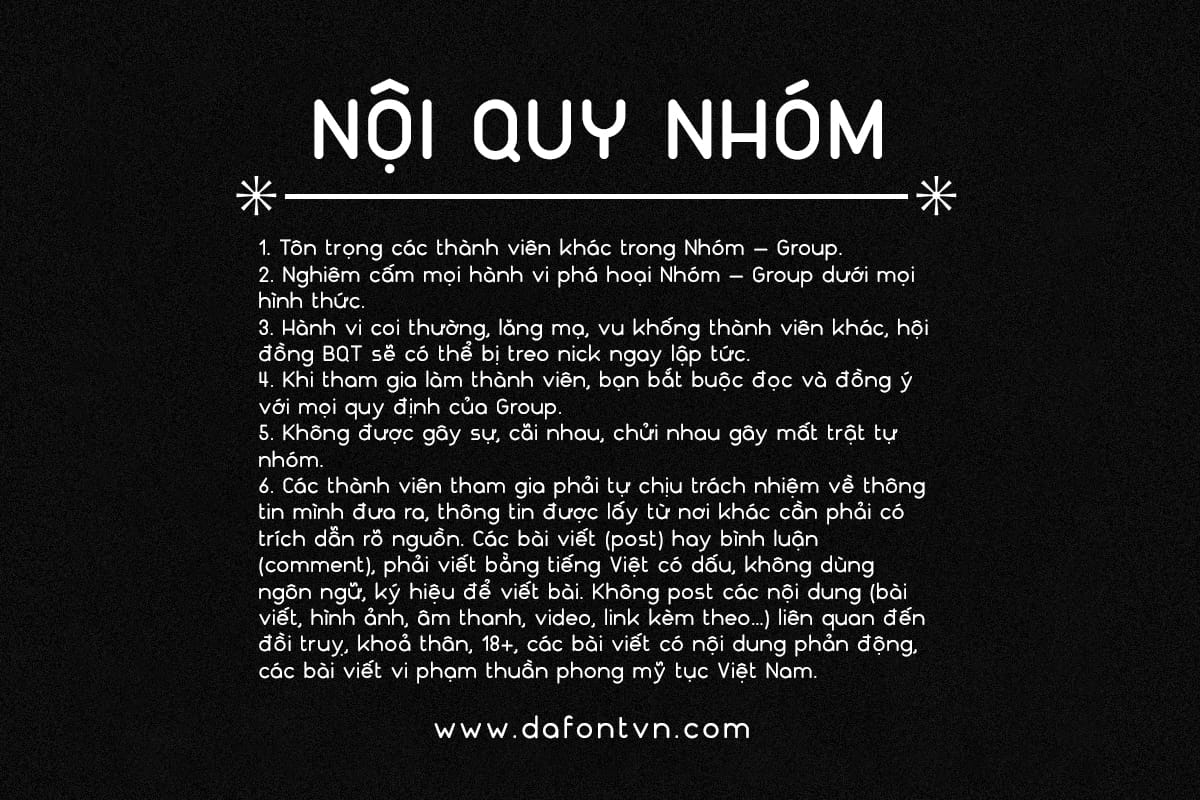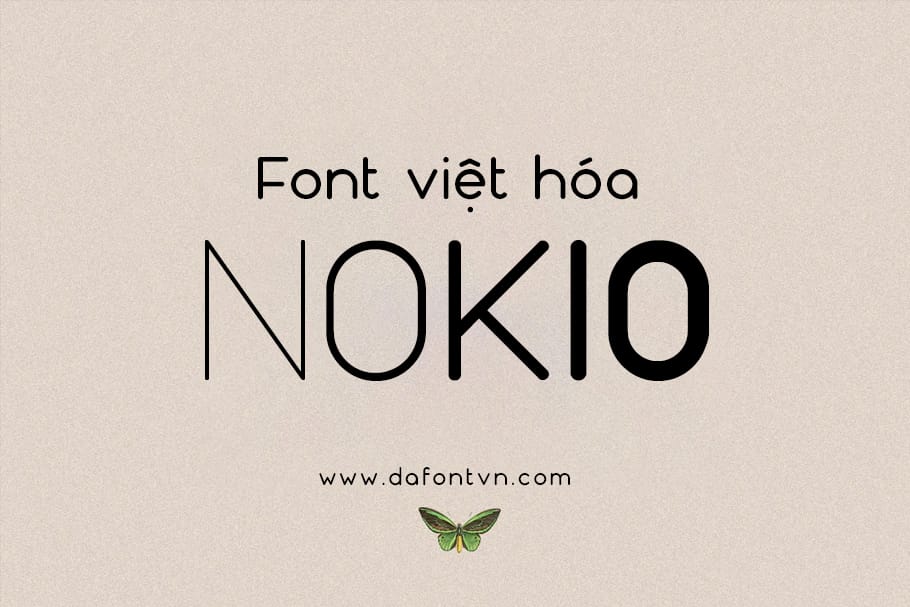
Nokio là một kiểu chữ Sans Serif tròn trịa, gọn gàng, tối giản được thiết kế vào năm 2013 bởi TypeUnion. Nokio sử dụng các đường nét và đường cong rõ ràng phù hợp với nhiều thiết kế có cấu trúc với sự vui tươi tinh tế.